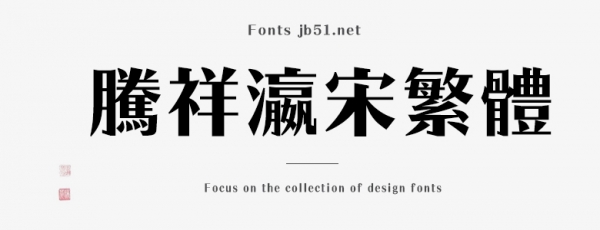
騰祥瀛宋繁-W9是一款不錯的藝術(shù)字體,由騰祥字庫出品,這款字體筆觸略顯粗實,字形端正,適合應(yīng)用于藝術(shù)設(shè)計、平面宣傳設(shè)計、網(wǎng)頁設(shè)計,書法字帖等領(lǐng)域,需要的朋友可以前來本站下載。
此款字為騰祥瀛宋系列字庫,是騰祥公司自主精心設(shè)計開發(fā)的精品正文字庫。一共10款粗細(xì),以期滿足用戶不同領(lǐng)域的用字需求。此款字為瀛宋W9,可用于正文、大標(biāo)題等。整個系列字庫風(fēng)格完全一致,不管是常用字或是非常用字,字字精美、結(jié)構(gòu)端正、重心平穩(wěn)、美觀實用。此款字為騰祥公司推送《2019森澤字體大賽》參賽作品。